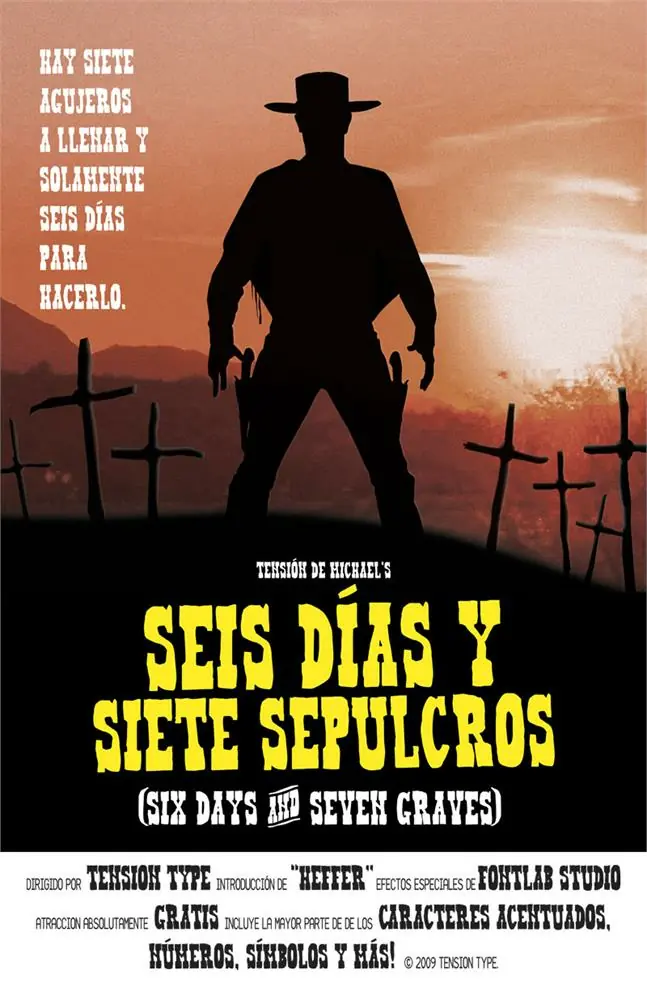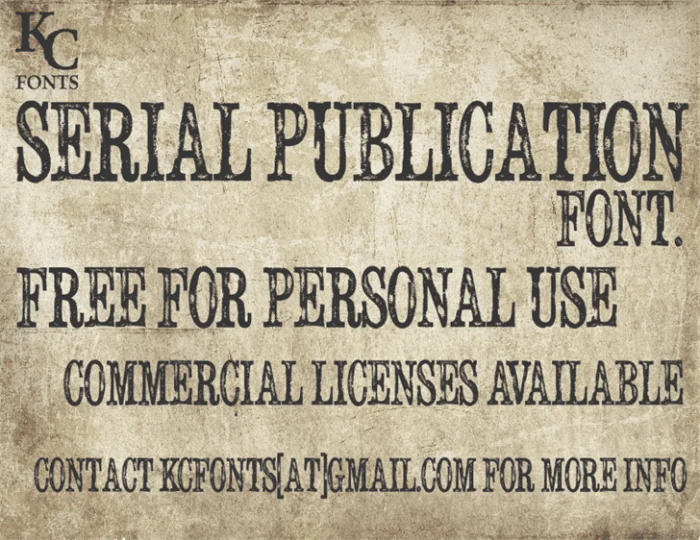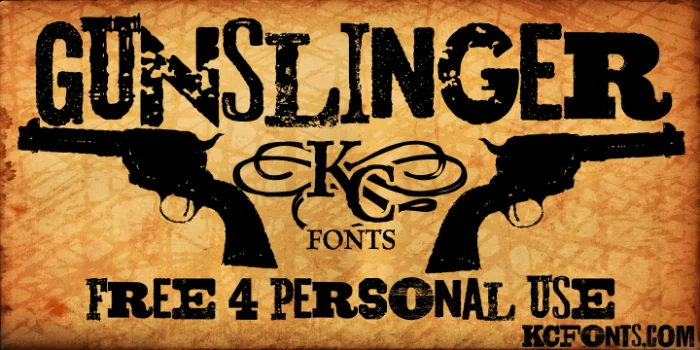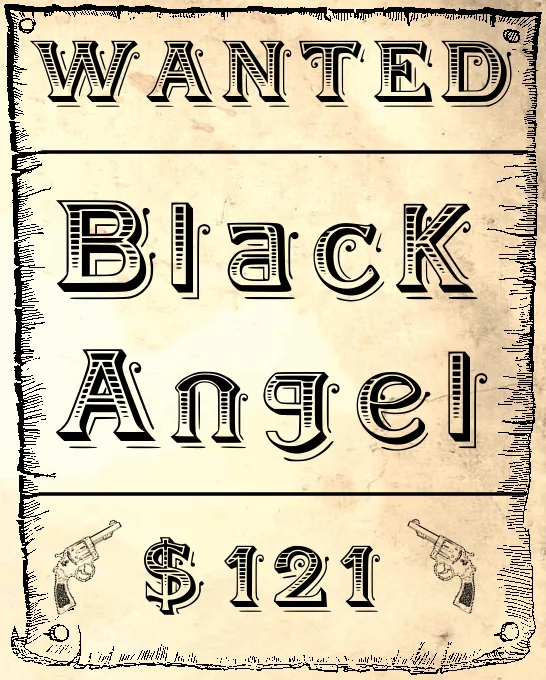
Tipografías del oeste verificadas
BlackAngel
Fuente tipo cartel de «se busca», con serifas gastadas que recuerdan a la madera envejecida de un saloon. Gratis solo para uso personal. Para un proyecto de cliente, contacta al diseñador (fontden) para la licencia comercial.
Serial Publication
Letras condensadas de imprenta antigua, con el desgaste típico de un periódico del oeste americano. Gratis para uso personal. El uso comercial exige contactar antes al diseñador.
Gunslinger
Trazos gruesos y angulosos, pensada para titulares de cartel de rodeo o saloon. Gratis para uso personal, comercial bajo petición al autor.
HellDorado
Estilo típico de cartel de recompensa, con un desgaste marcado que funciona bien en fondos oscuros. Gratis para uso personal. Para uso comercial, escribe al diseñador.
Heffer
La primera de las tres con uso comercial garantizado desde el principio, sin tener que escribir a nadie. Letras gruesas, ideales para pósters y titulares grandes.
Tanomuze Cowboy: Wild West
Fuente «Wild West» con más de 18.600 descargas, gratis para uso personal y comercial sin restricciones. Mi favorita del listado para logotipos o carteles que necesiten verse profesionales sin depender de una licencia dudosa.
Carnivalee Freakshow
A pesar del nombre, se categoriza como fuente western además de circense: mezcla el cartel de feria antigua con el aire de saloon del oeste. Gratis para uso personal y comercial.
Western Sheriff
Diseño directo de placa de sheriff, con letras cuadradas y gruesas, típicas de una insignia. Gratis solo para uso personal. El diseñador (Sronstudio) vende la licencia comercial en su propia web.
Cómo elegir según tu proyecto
Para un logo de marca, prioriza algo limpio: Tanomuze Cowboy o Heffer funcionan mejor a tamaños pequeños que las más desgastadas. Para un cartel de evento tipo rodeo, feria o fiesta de pueblo, HellDorado o Carnivalee Freakshow tienen más carácter y aguantan bien a tamaño grande.
¿Cuál elijo si nunca he usado una fuente western?
Tanomuze Cowboy: es la más legible de las ocho y tiene la licencia más sencilla, sin letra pequeña.